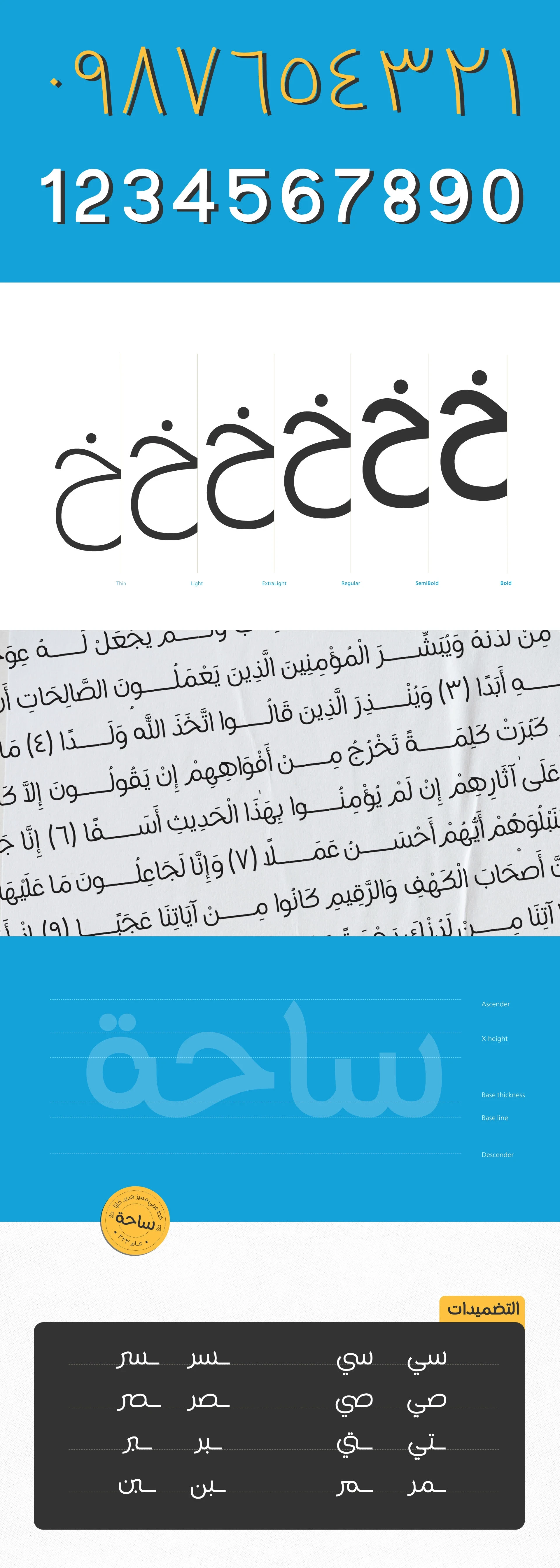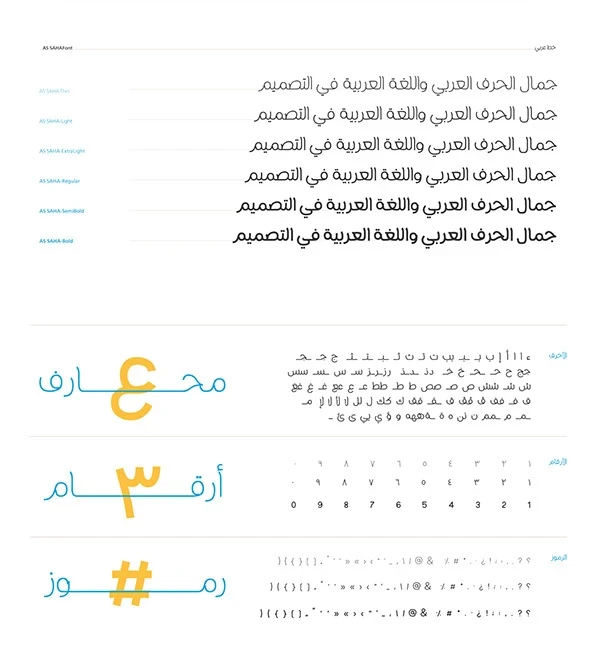
هو خط عربي هندسي معاصر، تم رسمه وبناؤه بعناية. تصميم الخط مستوحى من الأسلوب الخطّي العربي.
يتميز AS SAHA ببنية متساوية وتحكم بصري دقيق. تتكون أشكال الحروف من مزيج من الخطوط العمودية المستقيمة التي تتكامل بصريًا مع الزوايا الناعمة في بعض المناطق. وهذا يمنحه طابعًا طبيعيًا مناسبًا للتطور التكنولوجي والبصري في الوقت الحاضر.
تتنوع أوزان هذا الخط وتناسب استخدام الشركات في أسمائها ومظاهرها البصرية، كما أنه مناسب للعناوين والشعارات، ويُستخدم أيضًا في جميع متطلبات الإعلان والنصوص الطويلة، مثل العناوين، الشعارات، الهويات البصرية، الكتب، المجلات، الرسوم المتحركة، الويب والتلفزيون.
هو خط عربي هندسي معاصر، تم رسمه وبناؤه بعناية. تصميم الخط مستوحى من الأسلوب الخطّي العربي.
يتميز AS SAHA ببنية متساوية وتحكم بصري دقيق. تتكون أشكال الحروف من مزيج من الخطوط العمودية المستقيمة التي تتكامل بصريًا مع الزوايا الناعمة في بعض المناطق. وهذا يمنحه طابعًا طبيعيًا مناسبًا للتطور التكنولوجي والبصري في الوقت الحاضر.
تتنوع أوزان هذا الخط وتناسب استخدام الشركات في أسمائها ومظاهرها البصرية، كما أنه مناسب للعناوين والشعارات، ويُستخدم أيضًا في جميع متطلبات الإعلان والنصوص الطويلة، مثل العناوين، الشعارات، الهويات البصرية، الكتب، المجلات، الرسوم المتحركة، الويب والتلفزيون.
هو خط عربي هندسي معاصر، تم رسمه وبناؤه بعناية. تصميم الخط مستوحى من الأسلوب الخطّي العربي.
يتميز AS SAHA ببنية متساوية وتحكم بصري دقيق. تتكون أشكال الحروف من مزيج من الخطوط العمودية المستقيمة التي تتكامل بصريًا مع الزوايا الناعمة في بعض المناطق. وهذا يمنحه طابعًا طبيعيًا مناسبًا للتطور التكنولوجي والبصري في الوقت الحاضر.
تتنوع أوزان هذا الخط وتناسب استخدام الشركات في أسمائها ومظاهرها البصرية، كما أنه مناسب للعناوين والشعارات، ويُستخدم أيضًا في جميع متطلبات الإعلان والنصوص الطويلة، مثل العناوين، الشعارات، الهويات البصرية، الكتب، المجلات، الرسوم المتحركة، الويب والتلفزيون.